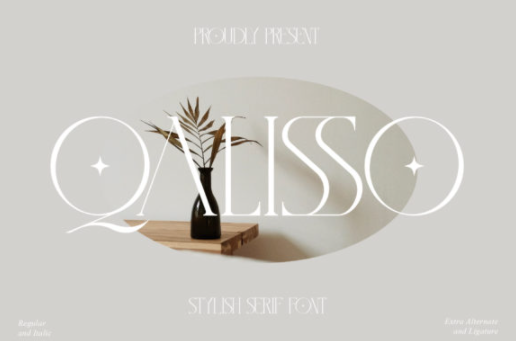
[Creativefabrica] Qalisso Font (2022)
Qualisso - это современный классический шрифт с засечками, обладающий уникальным стилем и современным видом.
Этот шрифт идеально подходит для элегантного и роскошного логотипа, дизайна названия книги или фильма, модного бренда, журнала, одежды, надписей, цитат и многого другого.
Qualisso - это современный классический шрифт с засечками, обладающий уникальным стилем и современным видом.
Этот шрифт идеально подходит для элегантного и роскошного логотипа, дизайна названия книги или фильма, модного бренда, журнала, одежды, надписей, цитат и многого другого.